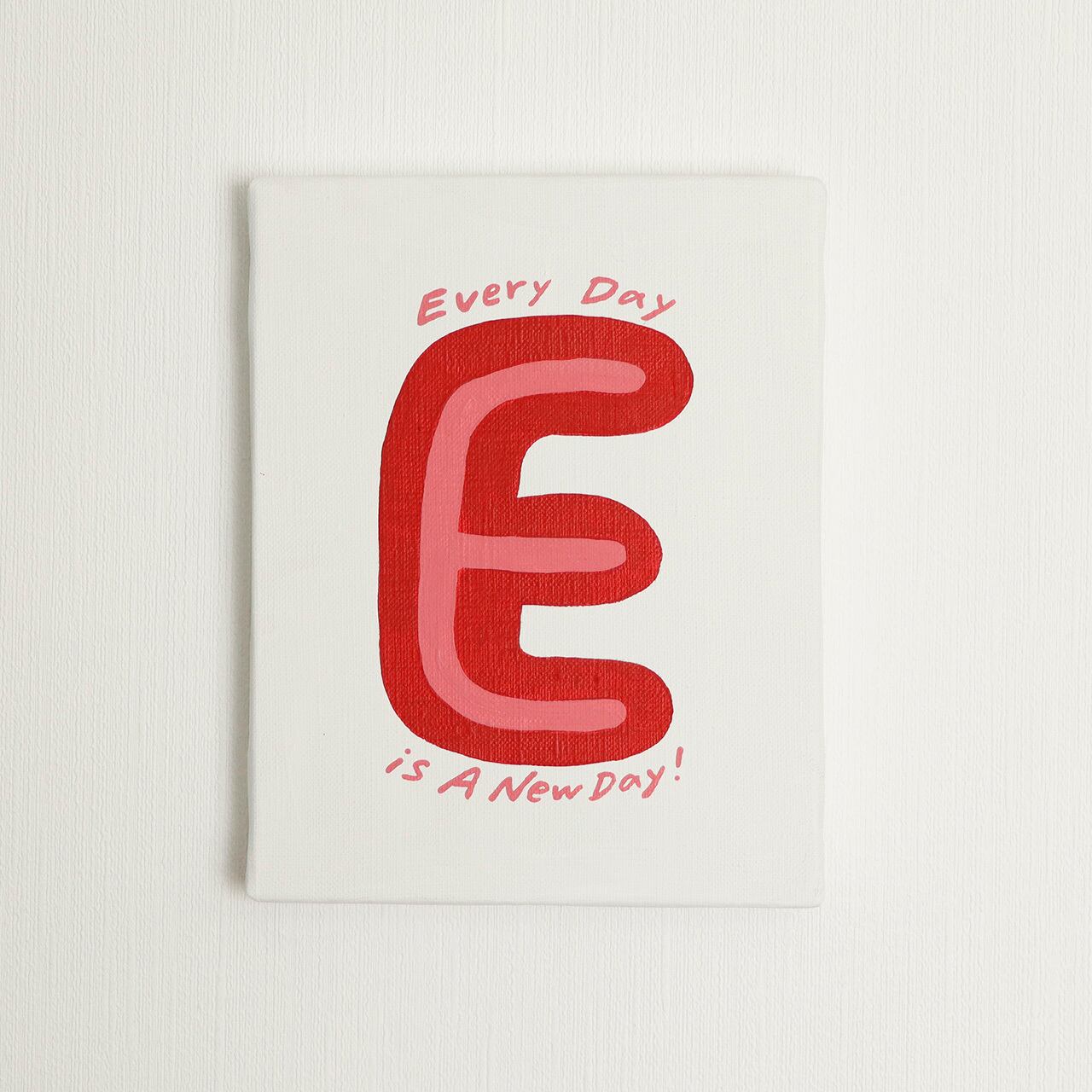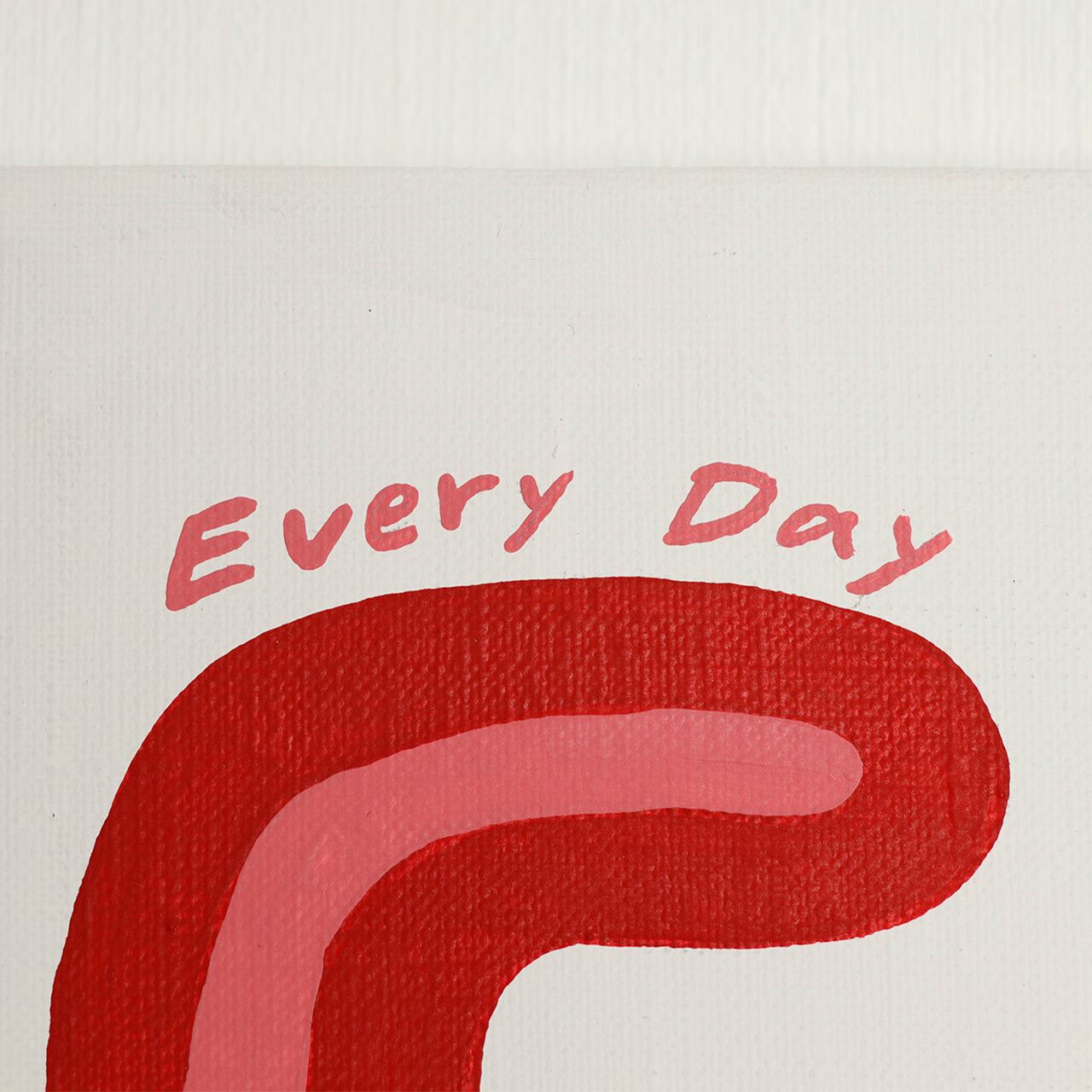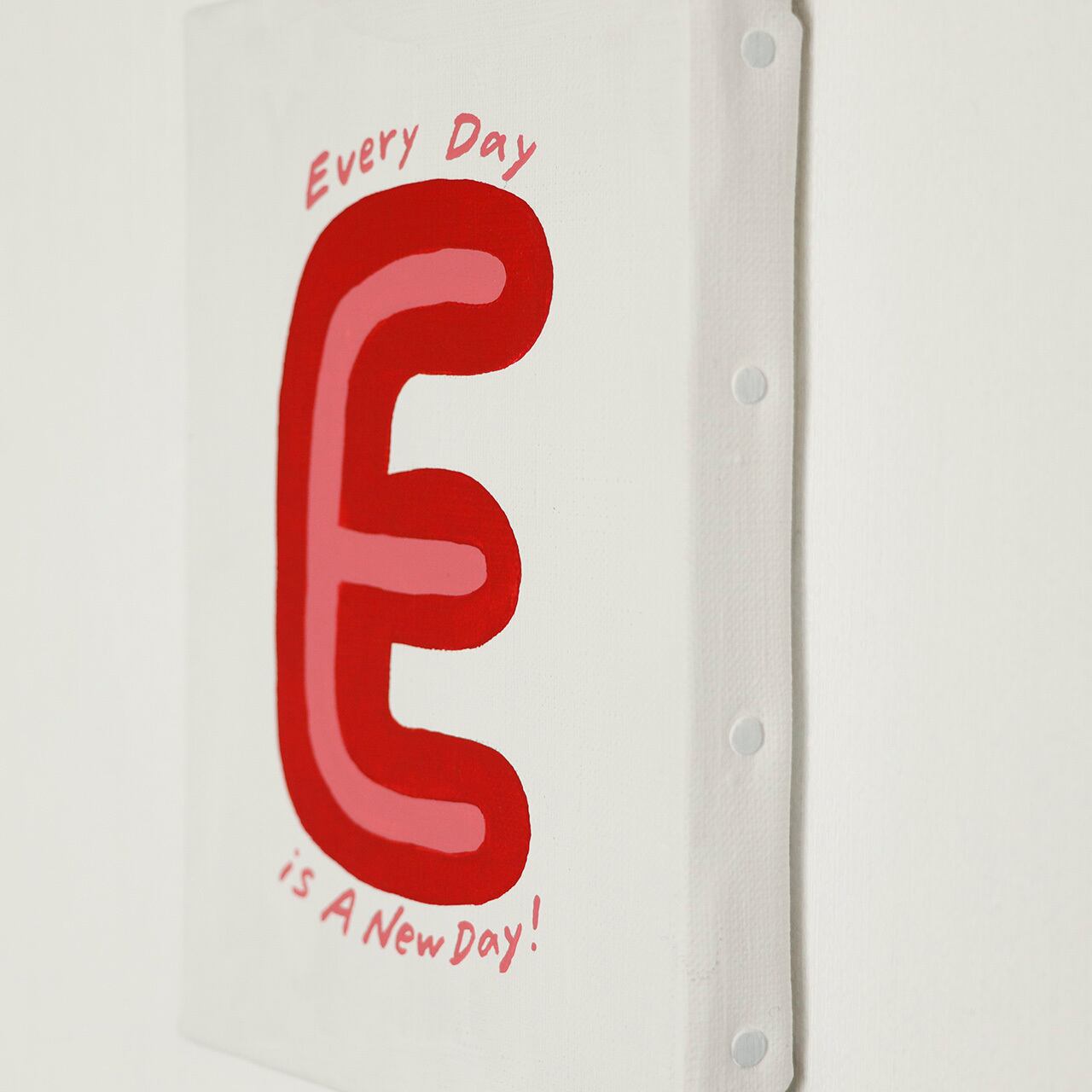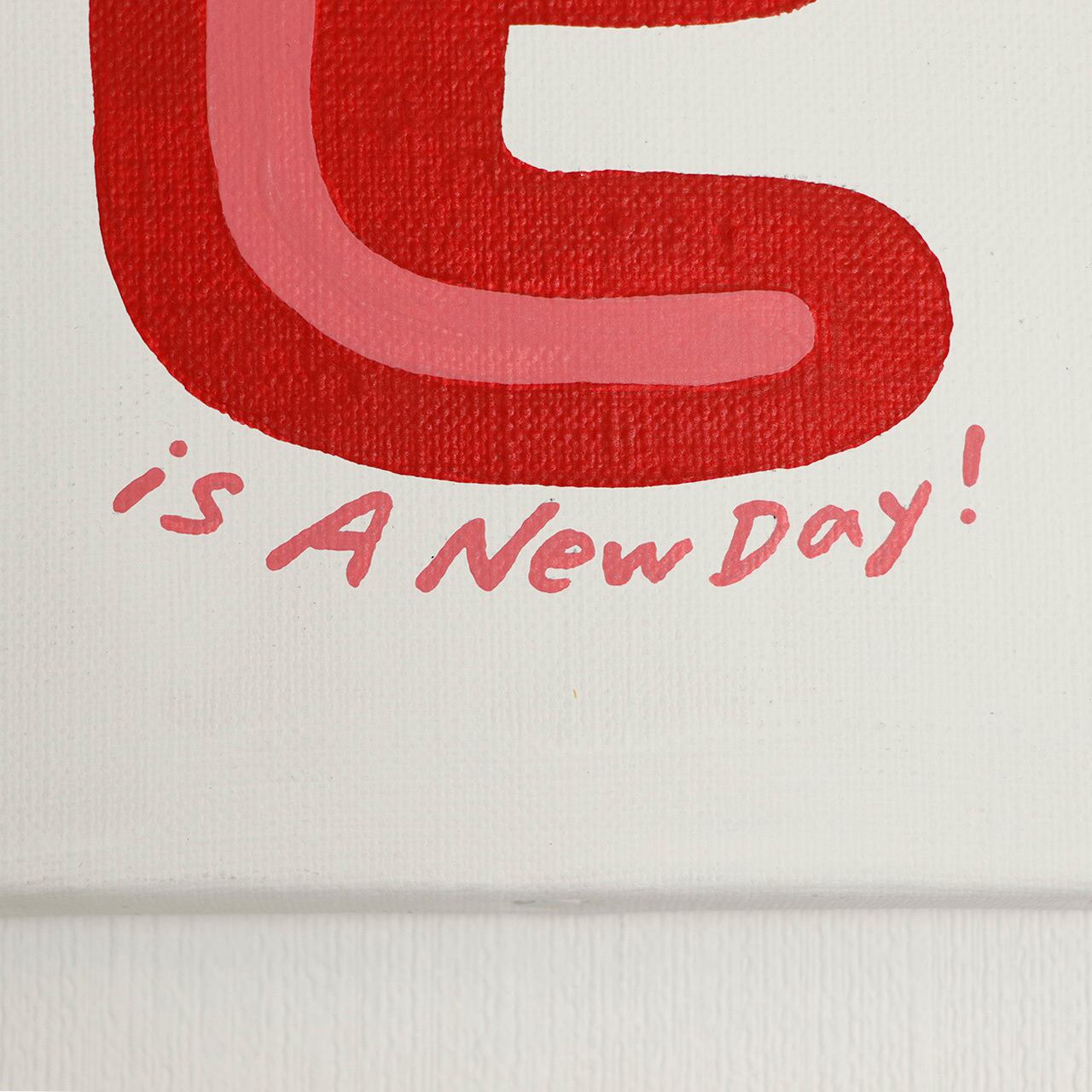
【E】Every Day is a New Day
とにかく、新しい毎日なんだ
イニシャルと、それから始まるちょっとポジティブなワードが入ったアートシリーズ。
この作品は一点ものです。白背景に大きくアルファベットを描いたこの作品は、どんな空間にもピッタリ。玄関やリビング・ベッドルーム、本棚にも◎好きな場所に飾りましょう!!
この作品で、見る人の気持ちがちょっとだけでもポジティブになれば嬉しいです^^